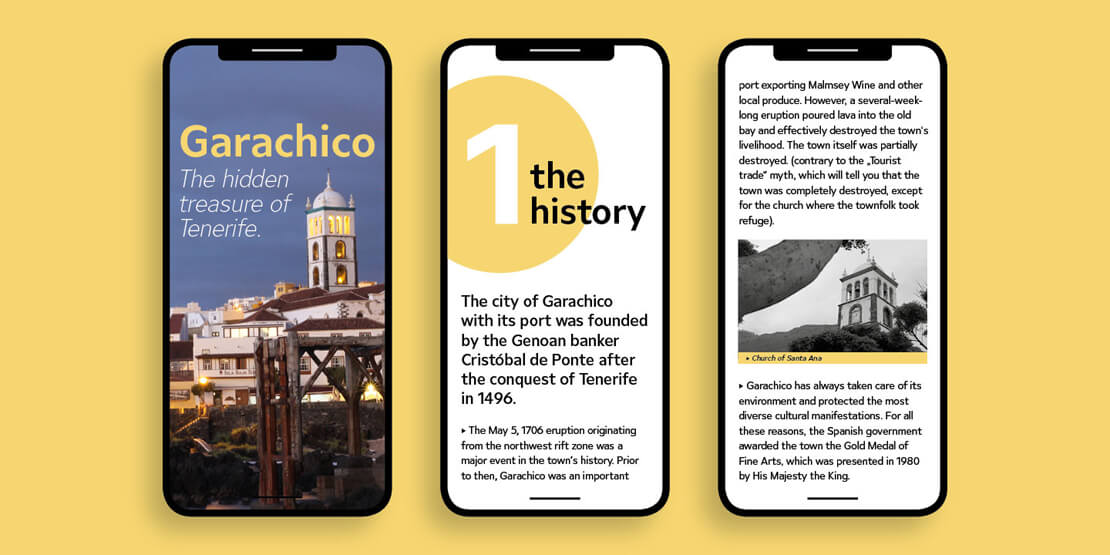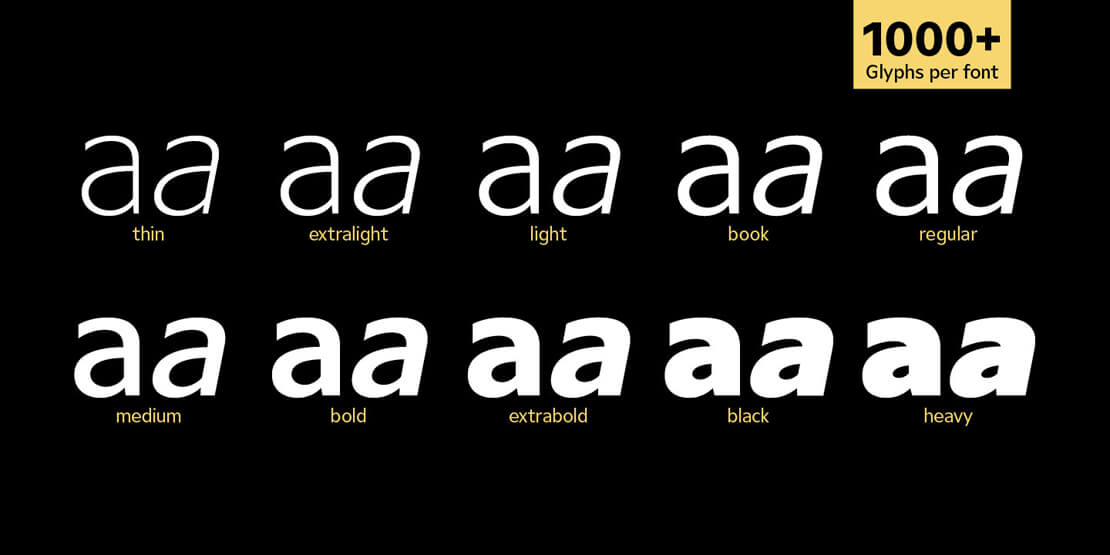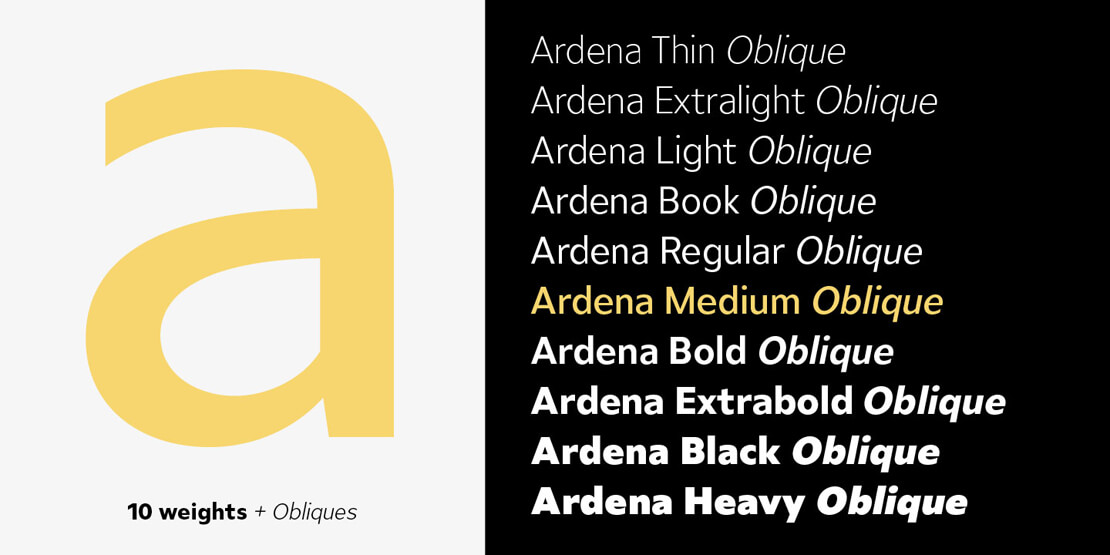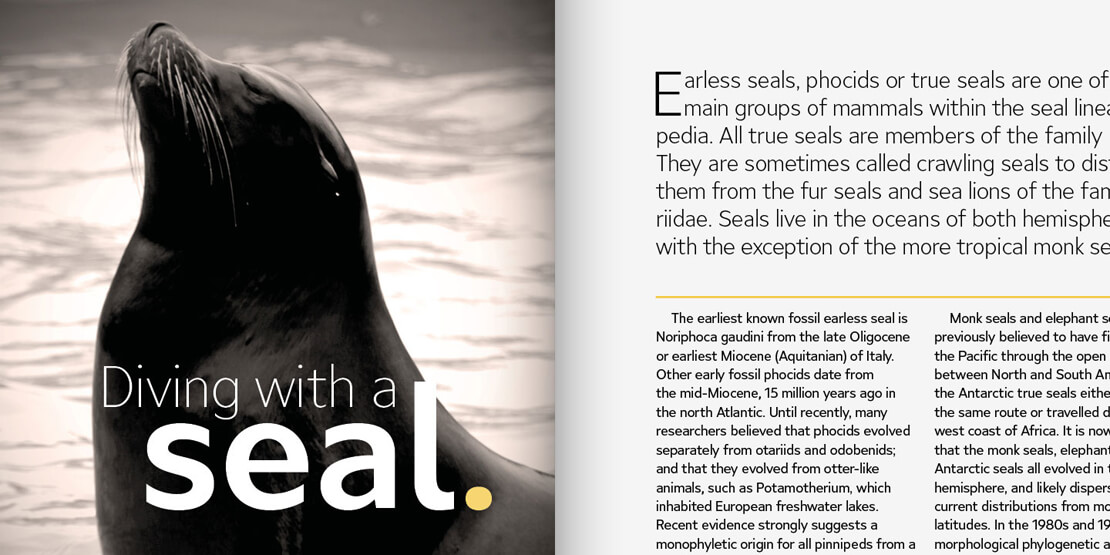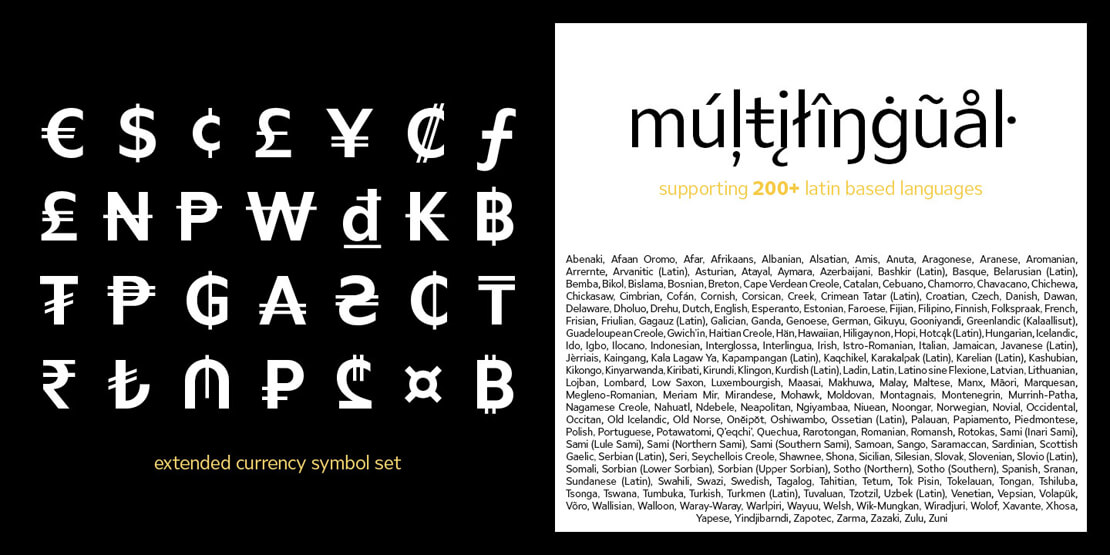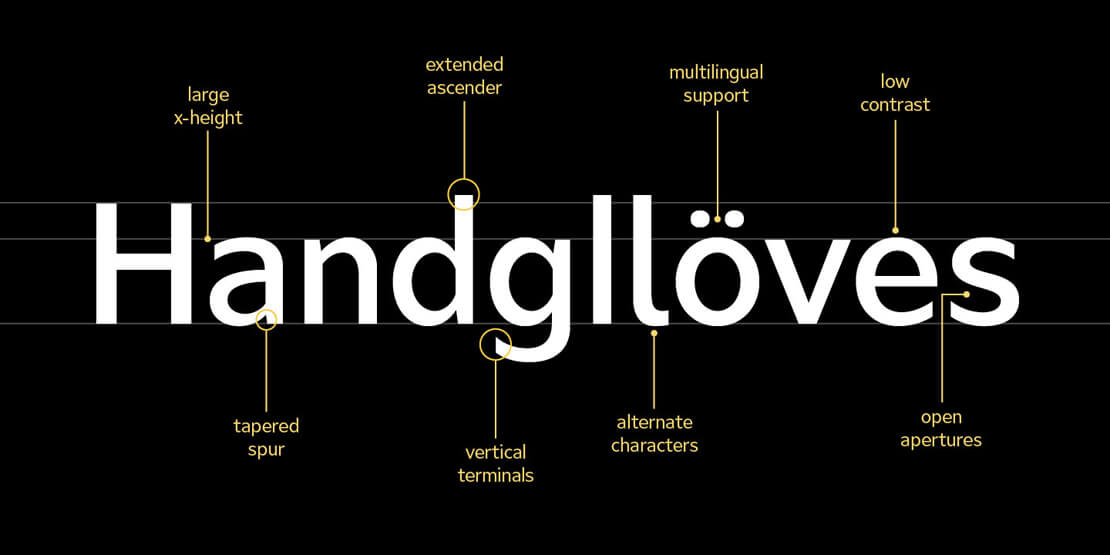
Ardena: Moderne Sans-Serif-Schriftfamilie
Julien Fincker hat eine umfangreiche Serifenlose mit vielen Features gestaltet. »Ardena« umfasst 20 Schnitte, über 1.064 Zeichen und deckt mehr als 200 lateinbasierte Sprachen ab.
Auf den ersten Blick neutral und klar, lässt sich die Schriftfamilie durch ihre offenen, runden Formen und vertikalen Endungen sowohl als freundlich, als auch souverän charakterisieren. Sie kann je nach Anlass eher zurückhaltend oder expressiv wirken. Ein vielseitiger Allrounder für Corporate Identity, Editorial, Branding, Leitsysteme und mehr.
Umfangreiche Features
Die Schnitte reichen von »Thin« bis »Heavy«. Außerdem stehen passende kursive Fonts zur Verfügung. Enthalten sind zudem viele Währungszeichen und Opentype-Features. Es gibt beispielsweise alternative Zeichen als Stylistic-Sets, Small Caps und automatische Brüche.
Ein besonderes Augenmerk hat Julien Fincker auf die Gestaltung von Pfeilen und Nummern gelegt. Durch Opentype-Features und einer nachvollziehbaren Systematik lassen sich die verschiedenen Ausführungen auch einfach »schreiben«, ohne sie erst in einer Glyphen-Palette auswählen zu müssen.
Das Prinzip: Steht eine Zahl zwischen einer runden oder eckigen Klammer, erscheint diese automatisch im konturierten Kreis oder Quadrat. Fügt man der Zahl noch einen Punkt hinzu, erscheint die Zahl in einem vollflächigen Kreis oder Quadrat. Das gleiche Prinzip gilt entsprechend auch für die Pfeile. Die Pfeile selbst setzen sich aus Kombinationen von Größer-/Kleiner-Zeichen mit den verschiedenen Slashes oder Bindestrich zusammen.
Designprozess der Schriftart
Nach der eher serifenbetonten und kontrastreichen Schriftart Spitzkant war es für den Type-Designer an der Zeit, ein absolutes Kontrastprogramm zu gestalten. Es sollte eine kontrastarme Serifenlose werden. Eine, die für alle Zwecke einsetzbar und gut ausgebaut ist.
»Also begann ich mit den ersten Skizzen und es stellten sich schnell die ersten Fragen.«, so der Kreative. »Auch neutrale Serifenlose können charakterlich stark voneinander abweichen. Wie schließt man die Endungen ab – vertikal, diagonal oder doch horizontal? Geometrische oder humanistische Proportionen, Strichstärkenkontrast, weiche oder spitz zulaufende Rundungen – alles Merkmale, die eine ganz eigene Dynamik entwickeln können. Dadurch gleicht also nicht jede Serifenlose der anderen, wie es im Allgemeinen gerne behauptet wird. Charakterlich sollte sie freundlich und souverän/seriös zugleich wirken. Das versprach ich mir durch offene, runde Formen und vertikale Endungen.«
Da neutrale Schriften durch ihre klare Lesbarkeit gerne auch für Orientierungs- und Leitsysteme genutzt werden, sollte den Designern noch etwas mehr als nur die klassischen Zahlen und Pfeile an die Hand gegeben werden. Daher zeichnete Julien Fincker alternative Zahlen und Pfeile in Kreisen und Quadraten – positiv wie negativ.
»Da diese allerdings nicht erst umständlich in Glyphen-Paletten gesucht werden sollten, entwickelte ich dank Open Type Features ein System, wie diese Zeichen auch einfach „geschrieben“ werden können.«, erklärt der Type-Designer. »Ein hilfreiches Tool und ein bequemer Weg für Nutzer, um an die entsprechenden Zeichen zu kommen. Lediglich die Standard Ligaturen müssen aktiviert sein, was bei den gängigen Grafikprogrammen, wie der Adobe Cloud, ohnehin voreingestellt ist.«
Um die Schrift für alle Zwecke einsetzbar zu machen, wurde sie entsprechend ausgebaut und um umfangreiche Sprachunterstützung, viele Währungszeichen, alternative Buchstaben, Kapitälchen und weitere Features ergänzt. Auch das Interrobang fand seinen Platz. Dadurch wuchs die Zeichenanzahl schnell auf über 1.000 an. Auch eine Kursive wurde gezeichnet.